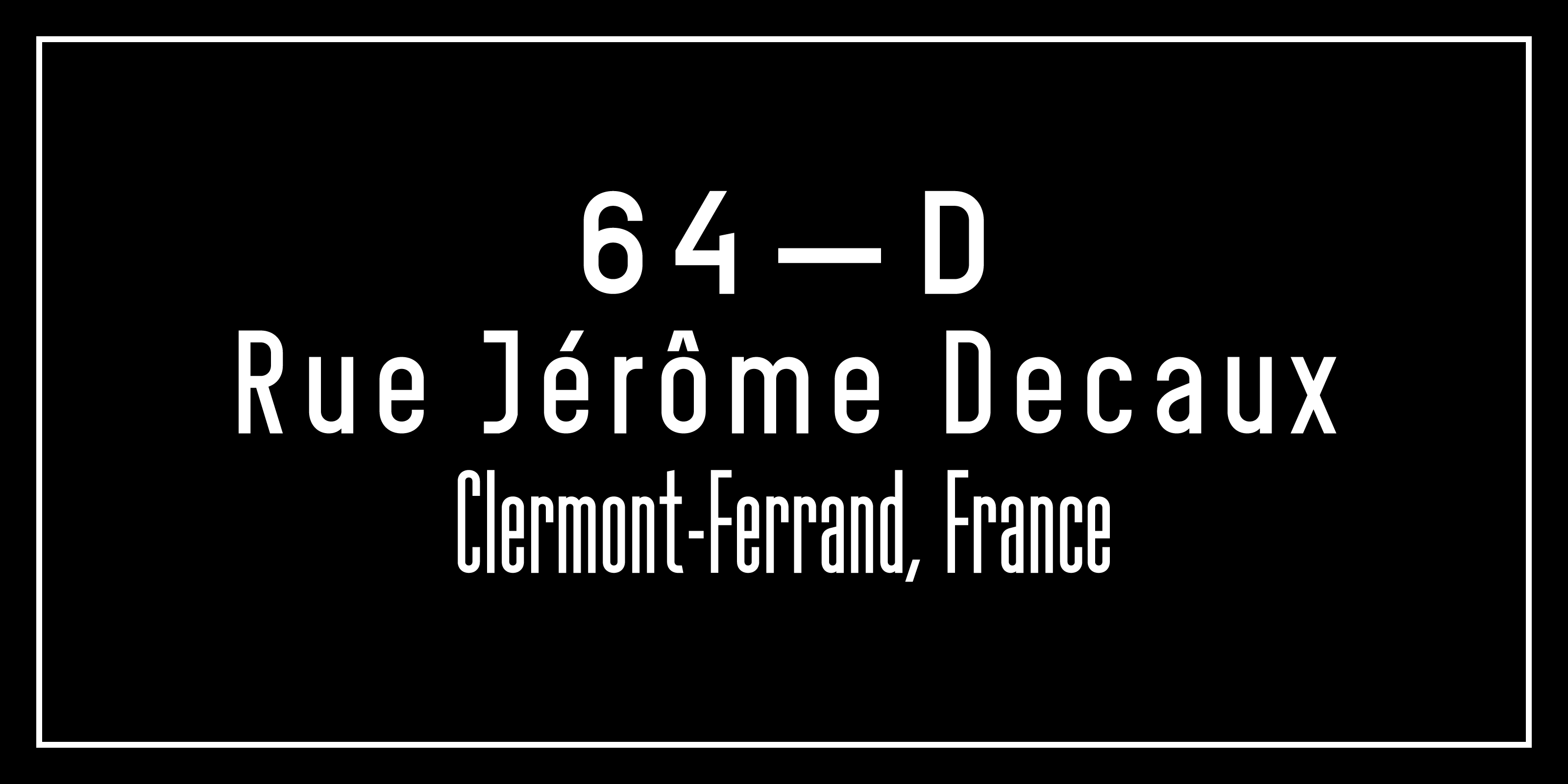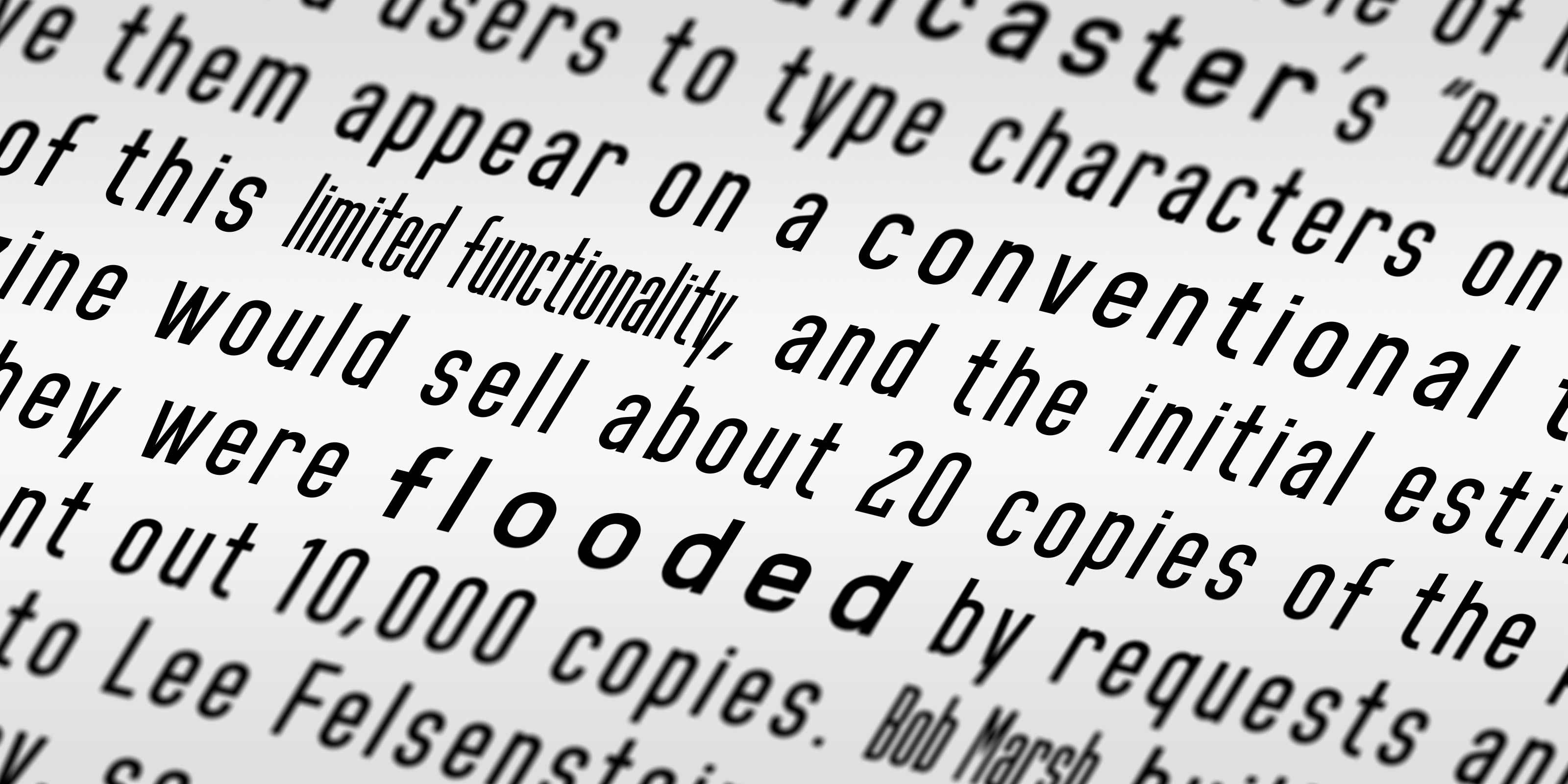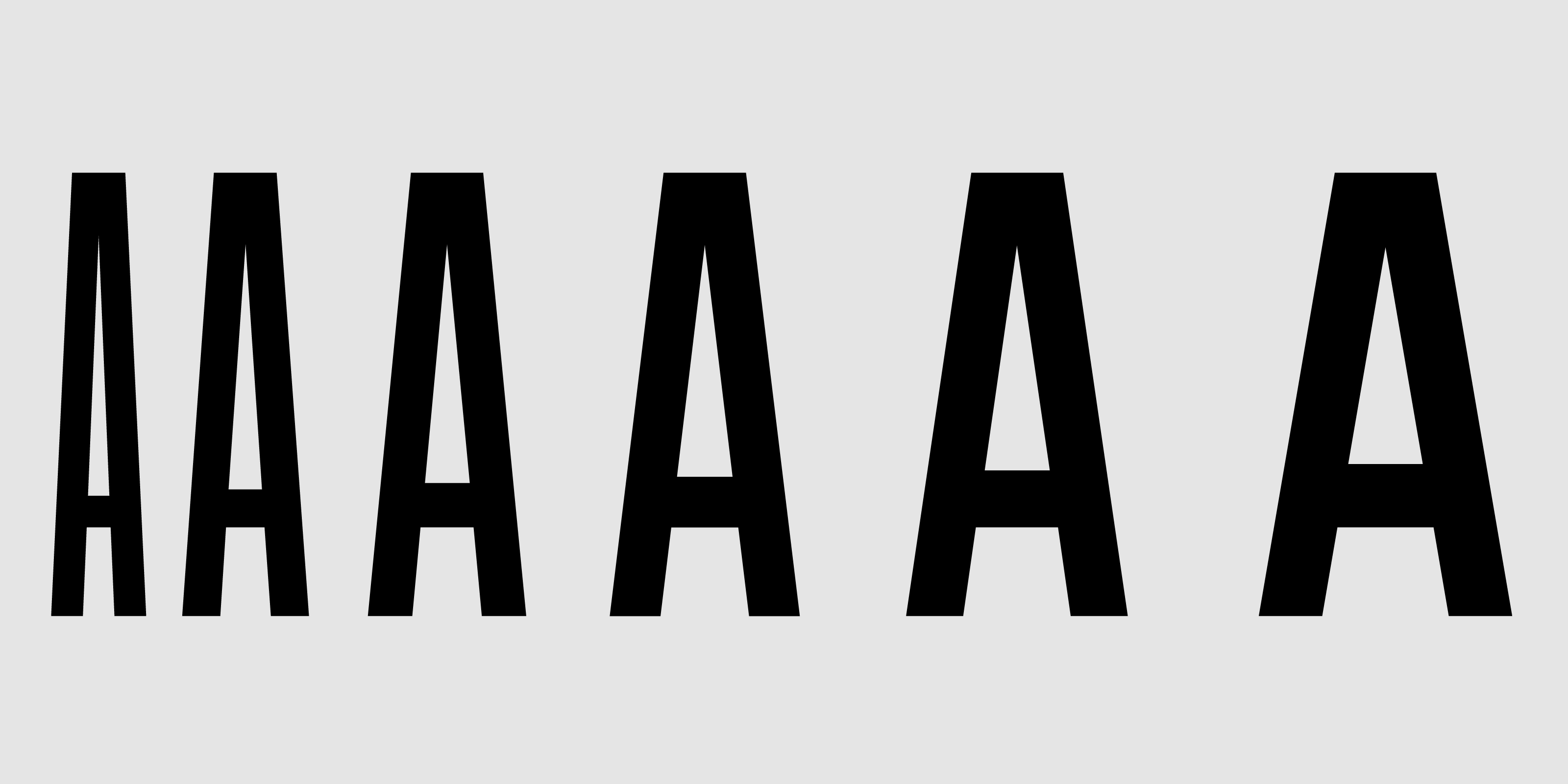
Tradičné písmo zo slovenských uličných tabuliek.
Manual Grotesk A je utilitárne geometrické sans-serifové písmo primárne určené pre použitie v nadpisoch, obsahujúc 6 štýlov, s žiadnym kontrastom, malou šírkou a vysokou strednou výškou.
Podporovanými znakovými sadami písma Manual Grotesk A sú základná latinka a rozšírená latinka, vďaka čomu môže byť písmo použité vo viac ako 100 jazykoch. S celkovým počtom 580 znakov, základnou sadou sú proporčné zarovnané číslice. Funkcie ako štylistická sada 1–6, malé kapitálky, všetky malé kapitálky a ordinály umožňujú ďalšie prispôsobenie a zvyšujú celkovú všestrannosť písma.
Písmo Manual Grotesk A takmer bez akýchkoľvek odchýliek vychádza pôvodnej predlohy ručne konštruovaného písma od Richarda Pípala z polovice 20. storočia.
Toto ikonické písmo, za socializmu prakticky všadeprítomné, a dodnes používané viacmenej už iba na označovanie slovenských ulíc, sa z verejného priestoru pomaly vytráca. Jeho digitalizácia je preto pokusom o jeho záchranu a zároveň aj snahou spopularizovať ho v novom kontexte.